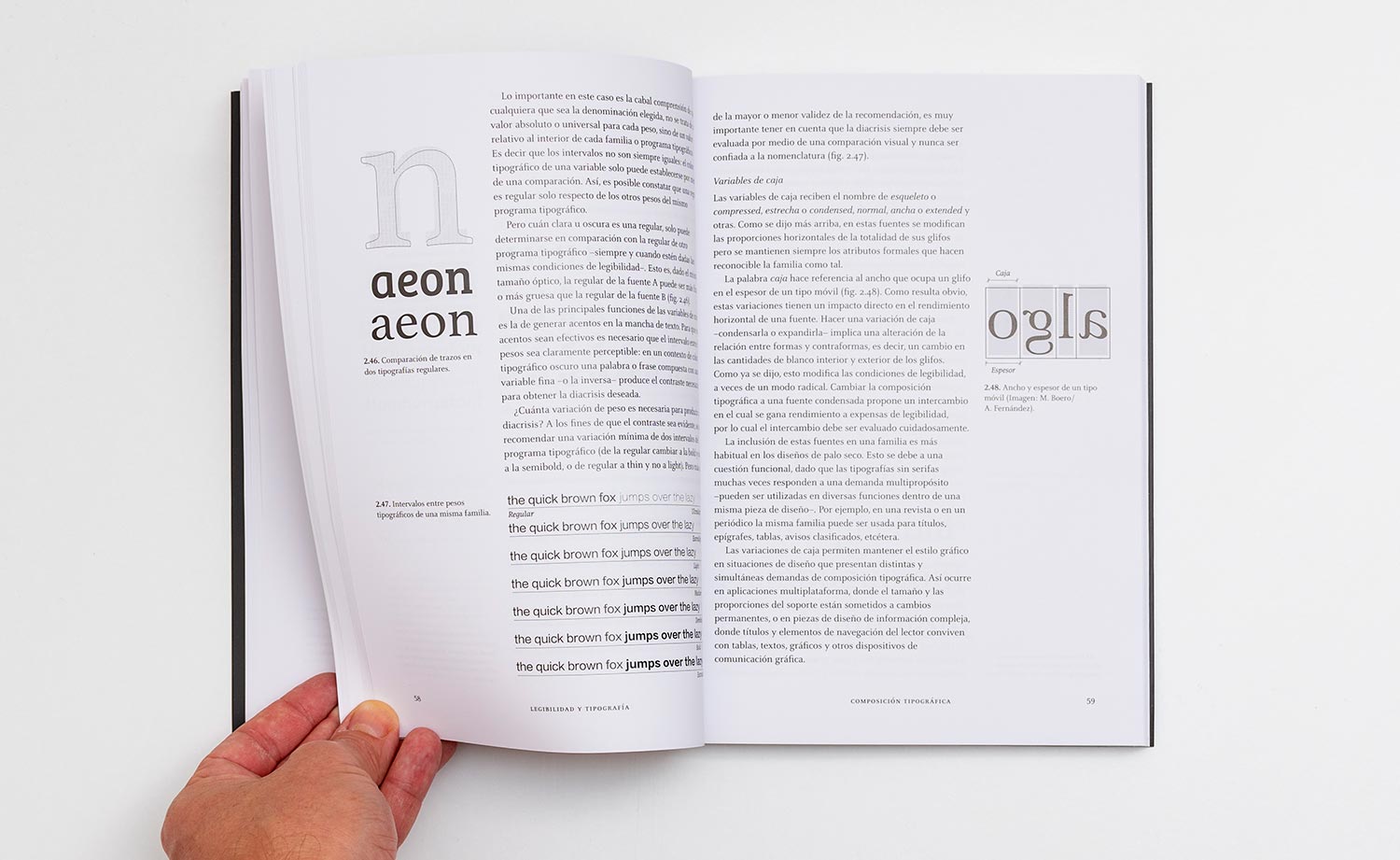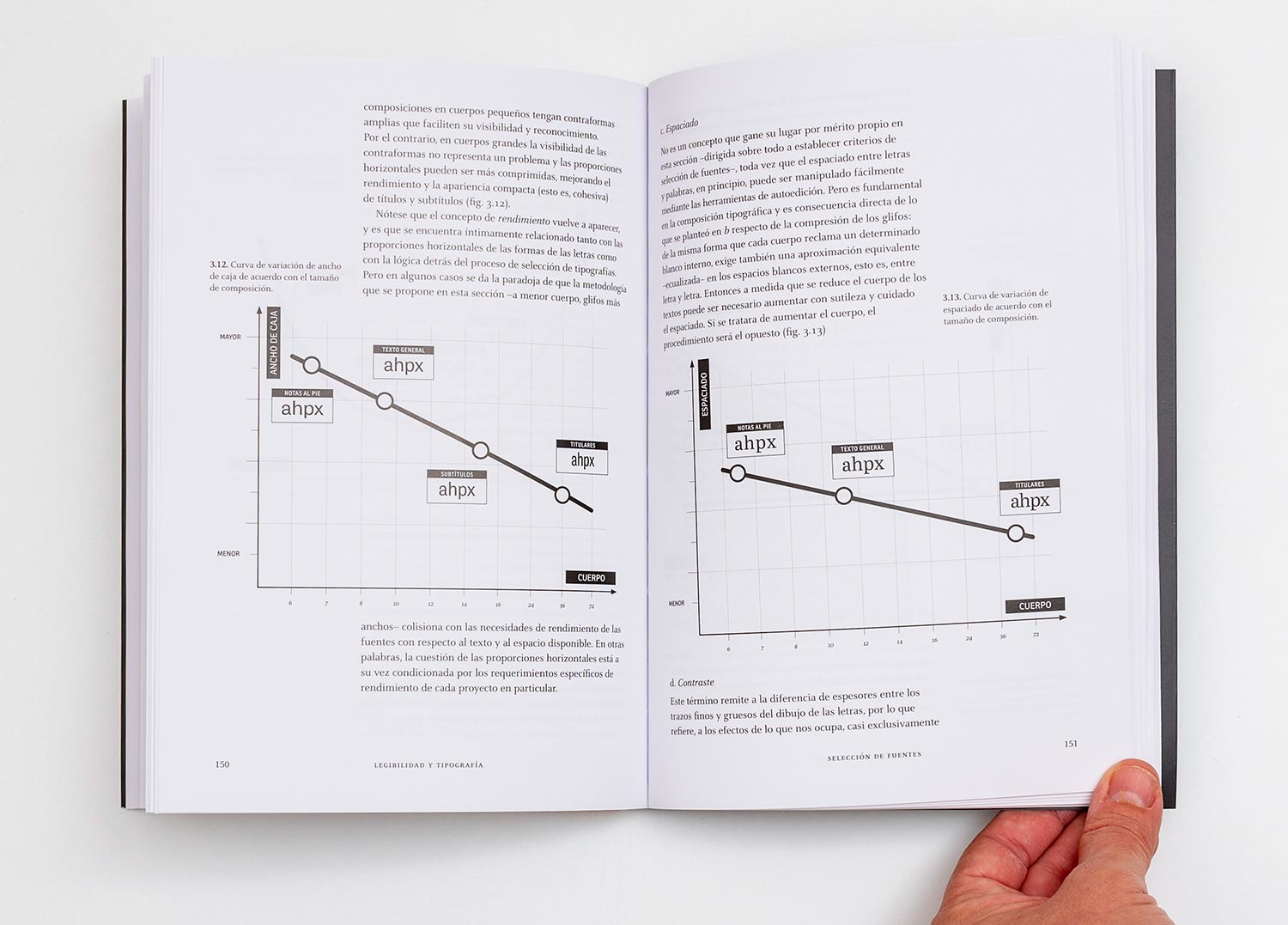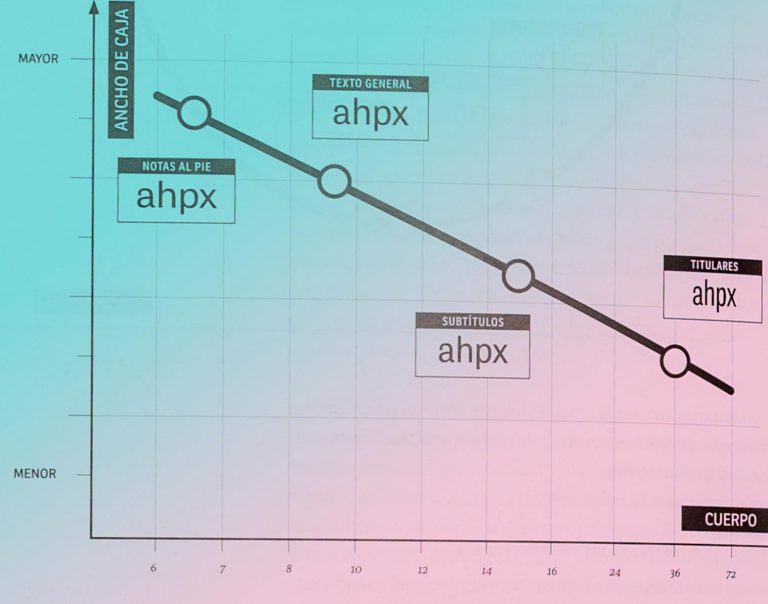
Legibilidad y tipografía. La composición de textos, editado por Campgràfic —una de nuestras editoriales de referencia, cartografía un mapa repleto de pistas para alcanzar un tesoro de lo más codiciado: comprender qué se esconde tras el término «legibilidad».
De esta forma, la obra nos provee de mayor criterio para tomar decisiones en torno a la composición de página. Casi nada amigxs.
Legibilidad y tipografía
Legibilidad y tipografía, fruto de 6 años de trabajo por parte de sus autores (Horacio F. Gorodischer y José Escaglione), parte de la premisa de definir lo que entendemos por «legibilidad». Para ello, se valen del sentido común y de la lógica tras las bambalinas de cualquier proceso de toma de decisiones donde intervenga el diseño editorial: la función manda.
La ausencia de verdades universales, precisamente, es la que nos conduce al necesario análisis de los factores que intervienen en la elección tipográfica. Asuntos como la naturaleza narrativa, la identificación de las unidades lógicas, la jerarquía o los componentes formales de la micro y macrotipografía, se analizan y ejemplifican a lo largo de este libro.
Legibilidad y tipografía no se compone de un conjunto de tips, ni es una suerte de «Composición para dummies»… La sensibilidad tipográfica, santo grial del diseño editorial, se adquiere a través del análisis concreto de cada original textual, pasándolo por el filtro de nuestro conocimiento tipográfico. Ni más ni menos.
«La legibilidad es la cualidad de un texto de ser leído y comprendido de la forma más apta de acuerdo con su función y con su naturaleza narrativa».Un análisis exhaustivo del universo tipográfico
La riqueza del contenido de Legibilidad y tipografía descansa, precisamente, en esta ausencia de reglas definitivas y absolutas, que conduce a Horacio F. Gorodischer y José Escaglione a construir un sólido background teórico. La incorporación de numerosos ejemplos visuales aportan un valor añadido enorme al conjunto.
Cuestiones como anatomía tipográfica, fuente, cuerpo, interlínea y su relación con el texto y con el ancho de columna, espaciado, alineación, así como un largo etcétera de lugares comunes en el desarrollo de la práctica editorial y tipográfica, desfilan en Legibilidad y tipografía tamizados por la premisa de su contribución a mejorar la legibilidad de nuestros textos, y diseñar páginas más atractivas, que cumplan a la perfección con su función divulgadora.
Gran valor pedagógico
Es capital resaltar la vertiente pedagógica de Legibilidad y tipografía. Para docentes especializadxs en diseño editorial —como es mi caso particular, resulta complicado hacer inteligible para lxs alumnxs la necesidad de elegir con precisión la tipografía ideal para cuerpos de texto.
Contar con un conglomerado de normas más explícitas en este sentido, nos ofrece la posibilidad de ahondar más y con mayor criterio en este aspecto central, no sólo en la confección de estilos de párrafo en InDesign, sino en la estética global que aportamos a nuestros diseños, así como otros aspectos determinantes a la hora de estudiar diseño editorial.
👉🏻 «La legibilidad es la cualidad de un texto de ser leído y comprendido de la forma más apta de acuerdo con su función y con su naturaleza narrativa».
👉🏻 «Comprensión no es —únicamente— entender lo que un texto dice sino entender lo que ese texto es».
👉🏻 «Una fuente está formada por un conjunto de signos que tiene el mismo ductus, o dicho de otro modo, que comparten una misma intención de diseño: están hechos conceptualmente por la misma mano y la misma herramienta».
👉🏻 «La dimensión de las líneas, debe contemplar también la estructura y el léxico del texto».
👉🏻 «La interlínea hilvana a los espacios blancos de la página, los articula y brinda coherencia y cohesión a la interacción entre llenos y vacíos de los diferentes elementos de la composición».
👉🏻 «La tipografía debe admitir todas las combinaciones posibles, dado que no se puede predecir la ilimitada cantidad y variedad de textos que pueden ser impresos con ella».
👉🏻 «No existe una legibilidad única aplicable a cualquier circunstancia. Es decir que cada texto —en su contexto— demanda sus propios atributos de legibilidad».
Conclusión
En definitiva, Legibilidad y tipografía cumple con creces con la premisa de su subtítulo —«La composición de los textos»— y aglutina en sus páginas secciones que favorecen la iniciación, el refuerzo y la profundización en el universo del diseño editorial y tipografía.
De esta forma, esta nueva pieza de Campgràfic va directa a engrosar nuestra biblioteca esencial de diseño editorial y tipografía, donde ya os hemos hablado con anterioridad de varias de sus referencias.
Los autores
Horacio F. Gorodischer es arquitecto y diseñador gráfico. Divide su actividad profesional entre la docencia de Diseño Gráfico, Tipografía y Ortotipografía en universidades de Argentina, España, México y Uruguay, y la divulgación en diversos medios especializados.